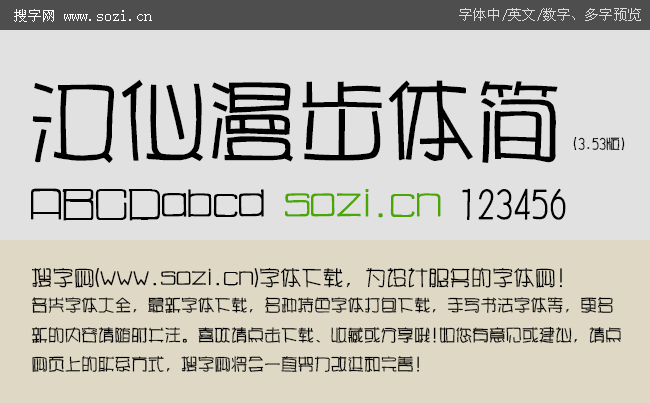
漢儀漫步體簡(jiǎn)
搜字網(wǎng)提供一款漢儀漫步體簡(jiǎn)中文藝術(shù)字體下載,漢儀漫步體簡(jiǎn)是一款POP風(fēng)格的藝術(shù)字體,字體俏皮可愛(ài),十分有趣,適合應(yīng)用于廣告設(shè)計(jì)、名片設(shè)計(jì)、包裝印刷、兒童產(chǎn)品設(shè)計(jì)等應(yīng)用。